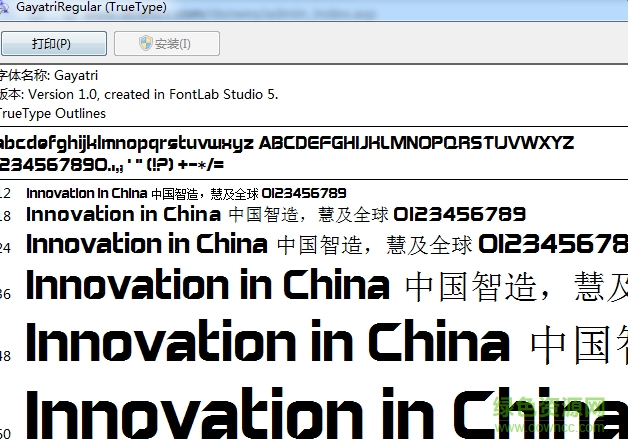
gayatri字體是一款極具個性的英文字體,文字排版、海報(bào)廣告設(shè)計(jì)、藝術(shù)設(shè)計(jì)等方面都可以使用,小編為大家?guī)砻赓M(fèi)下載地址,大家快來綠色資源網(wǎng)踴躍下載哦!
gayatri字體,一款非常好看的個性英文字體,字形工整大氣,書寫流暢,可用于排版方面。喜歡的朋友就趕快來綠色資源網(wǎng)下載使用吧!